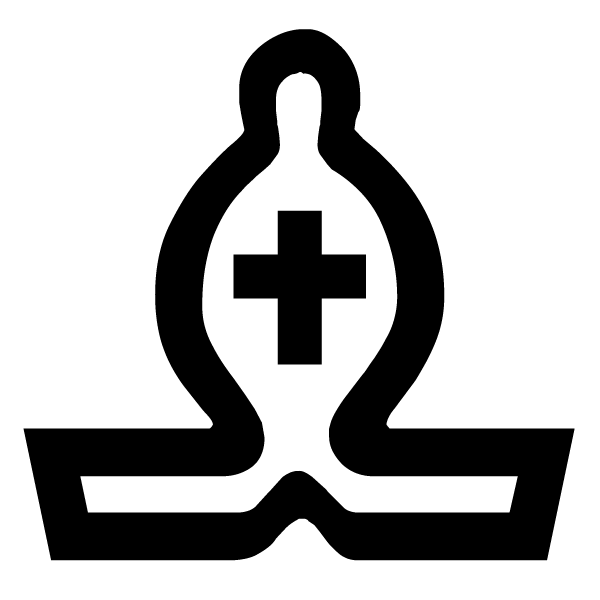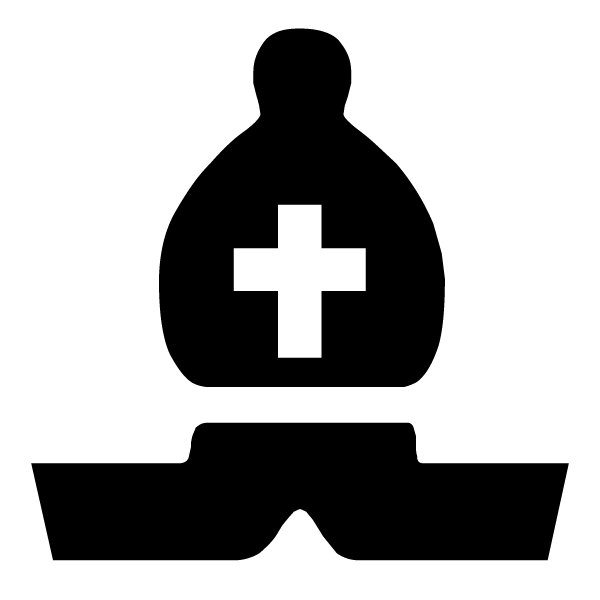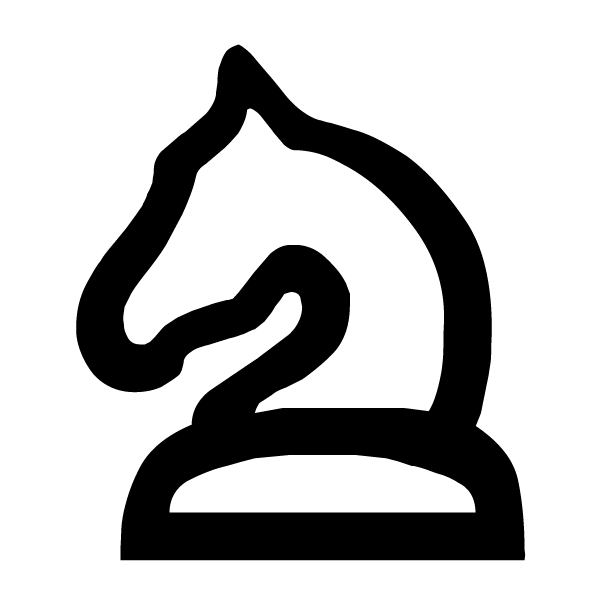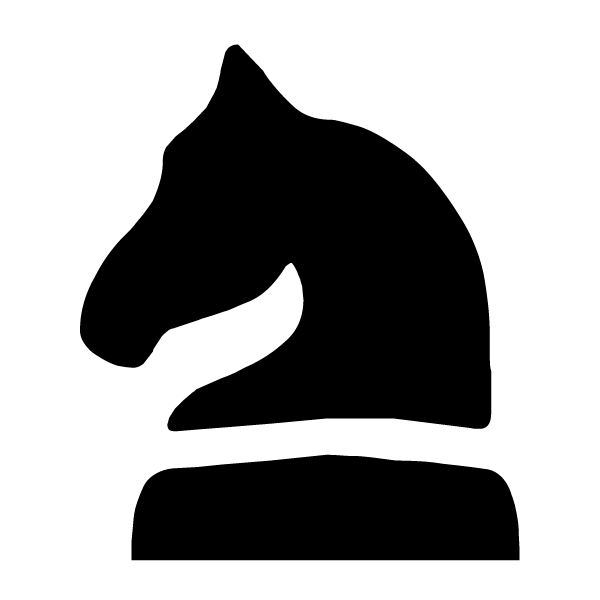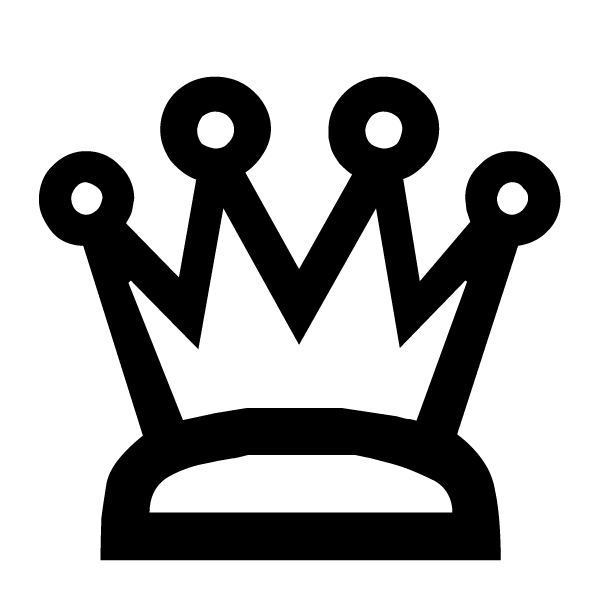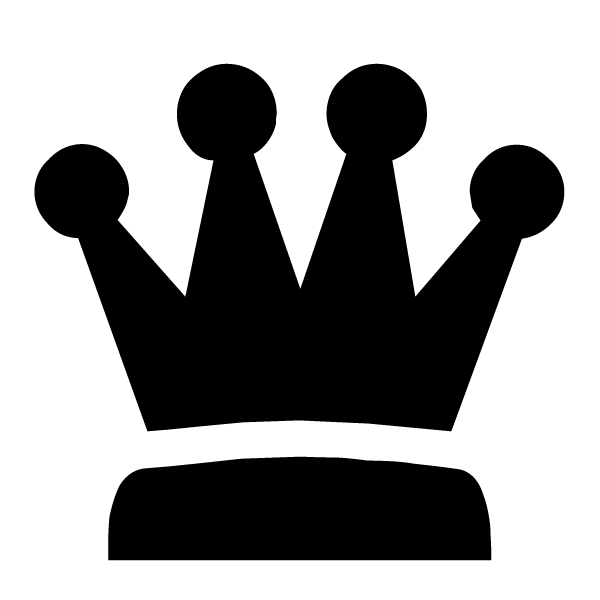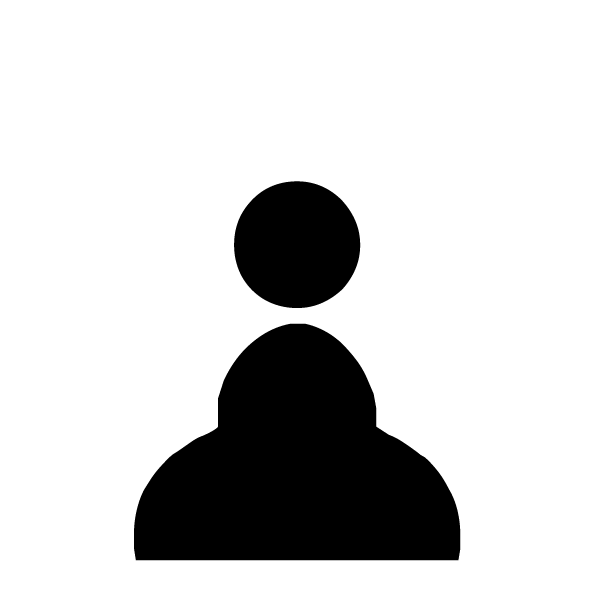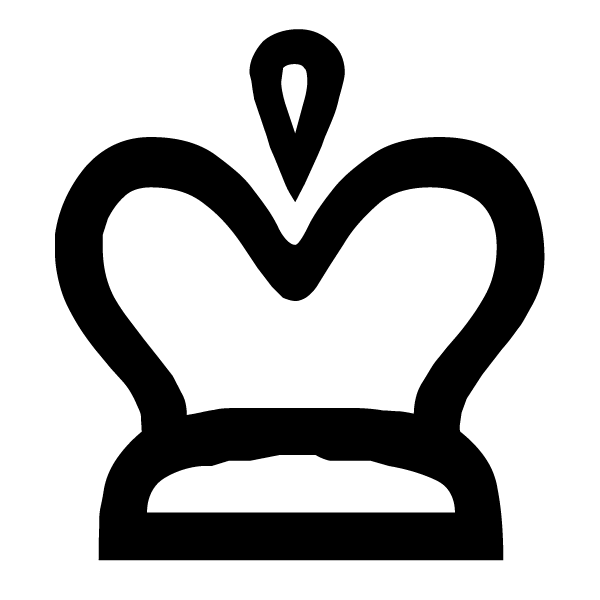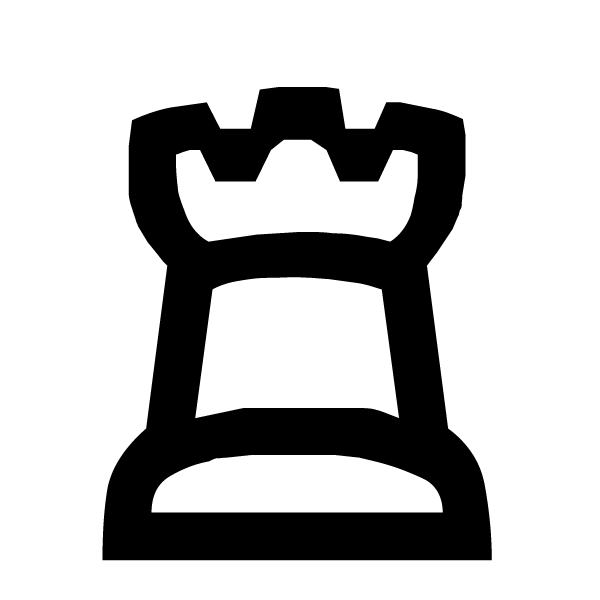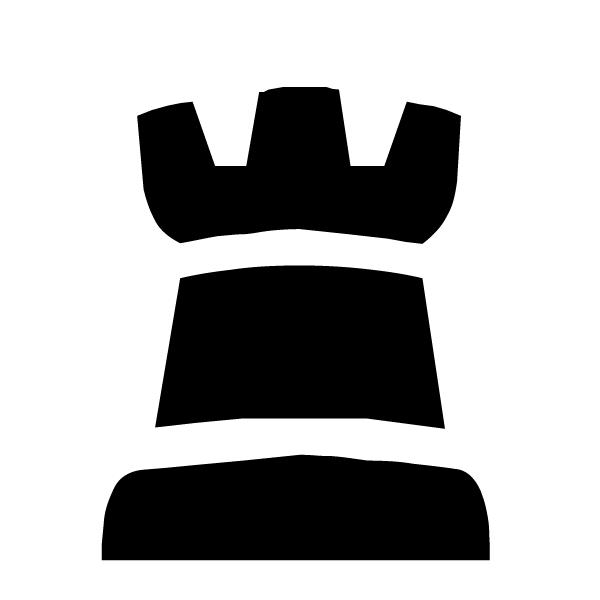
La Fuente Chess Usual se caracteriza por sus piezas definidas con un grueso borde que las distingue y les otorga un estilo sobrio y elegante. Esta fuente freeware, diseñada por Armando Hernandez Marroquin, es perfecta para quienes buscan un diseño claro y limpio para tableros, proyectos gráficos y documentos temáticos de ajedrez.
Juego de Ajedrez con la Fuente Usual: